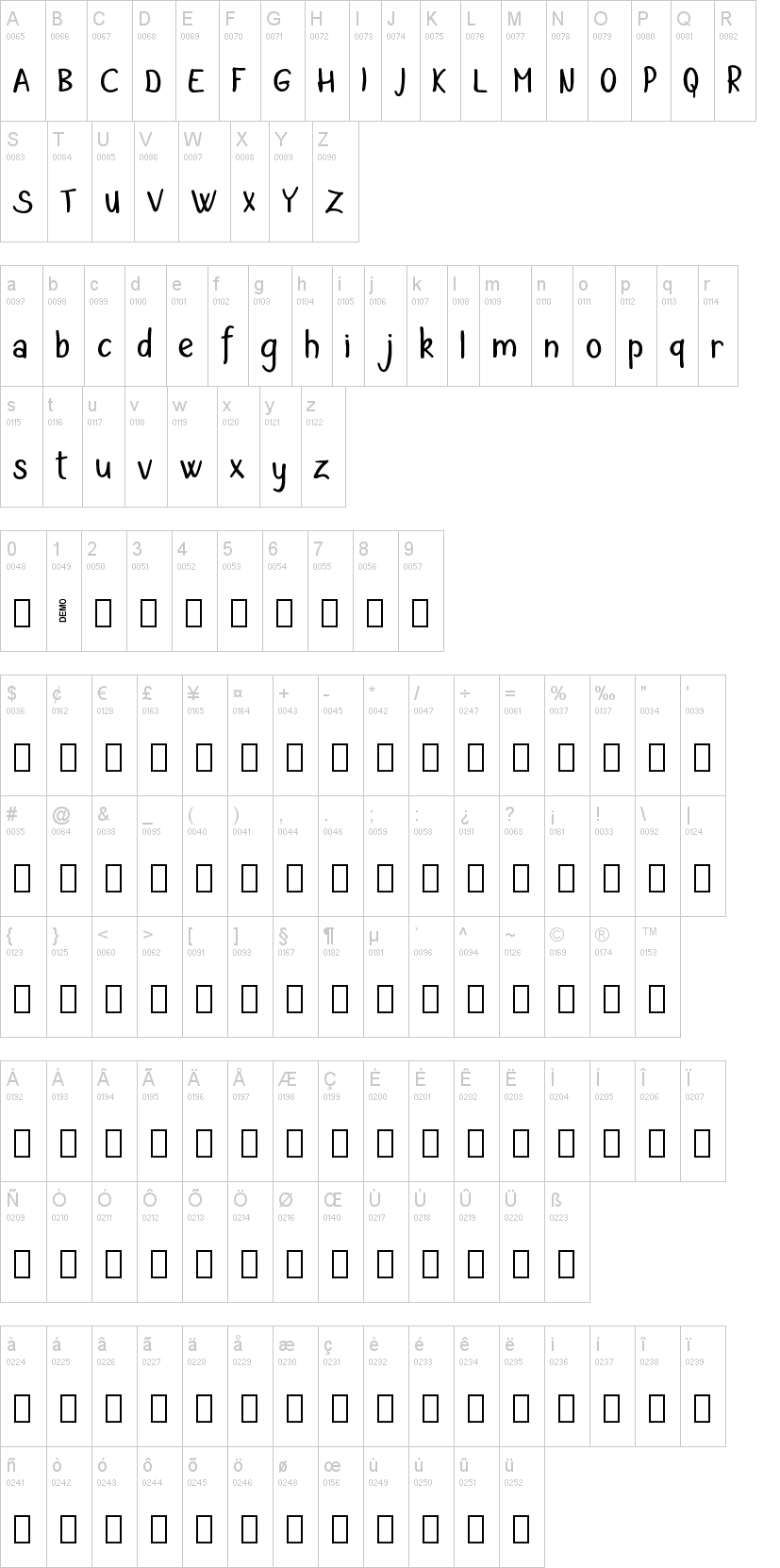
Balton 字体是一种非常漂亮的新型字体,它是由一位荷兰设计师开发的,它具有简洁、现代、优雅的特点,使用它可以让你的文本看起来更加清晰、简洁、大气,适合大多数流行的设计风格,是一种非常有用的设计字体。内容介绍
Balton是一款非常不错的手写艺术字体,具有很好的视觉感,适合于文化类的宣传设计、商业类品牌的广告和产品包装设计以及个性化文字排版等较多场景。